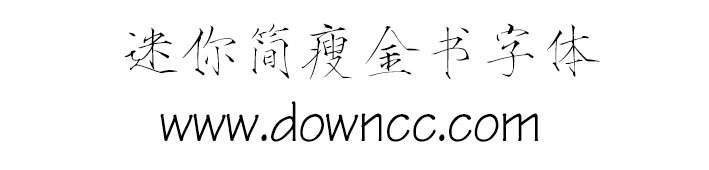
迷你簡瘦金書字體一款迷你字庫中的字體,瘦金體是宋徽宗趙佶創(chuàng)作的,是一款非常美觀的字體。非常適合用于名片設計、廣告設計、平面設計、雜志報刊等,有喜歡的朋友可以來綠色資源網(wǎng)下載使用!
迷你簡瘦金書字體從名字我們就可以聽出來,這款字體給人的整體感受就是瘦,細細的線條,看上去又是特別的有力。